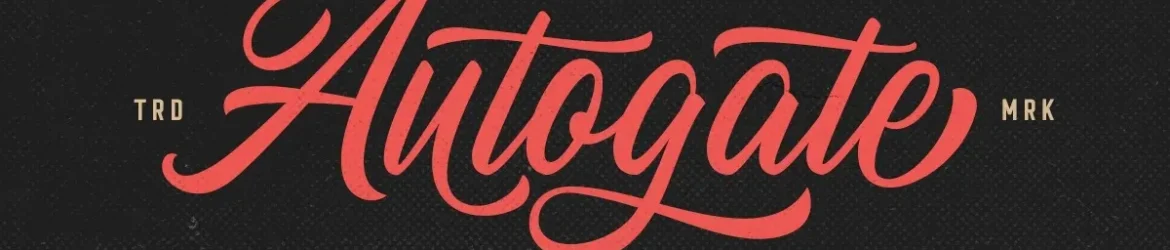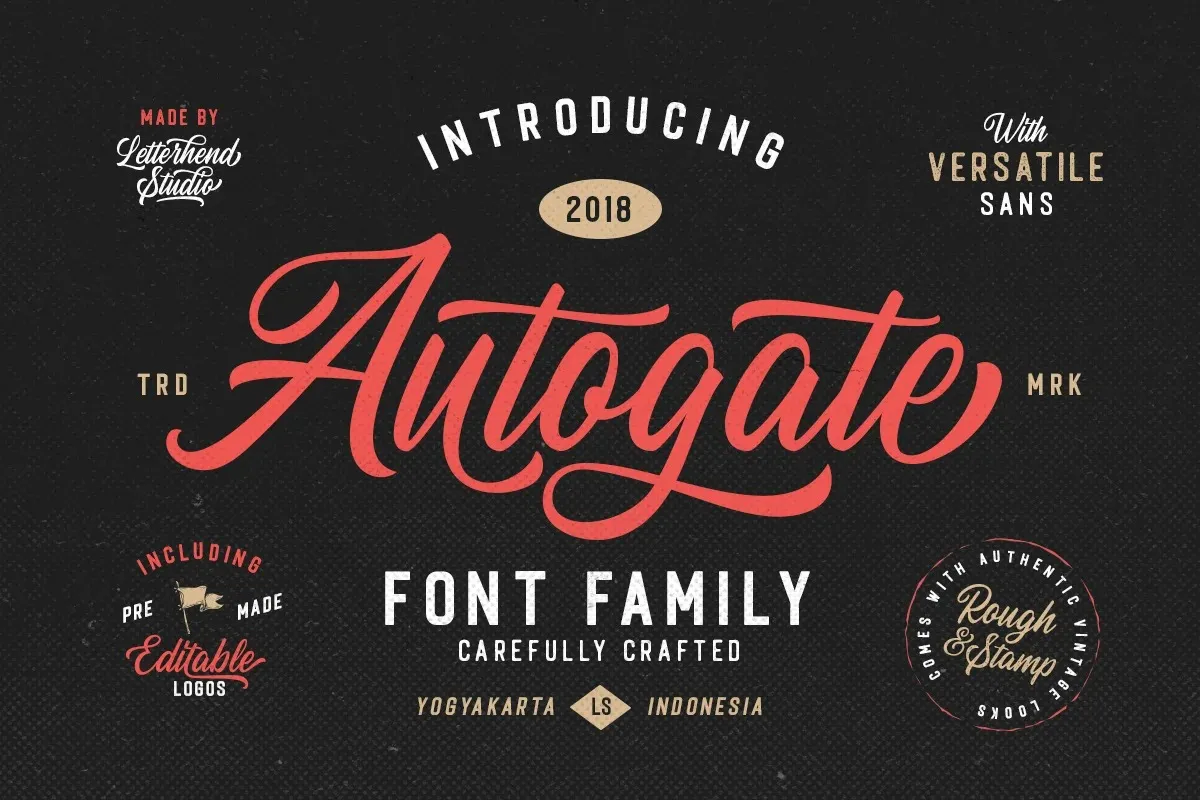
Autogate Font – Fonte Grátis
Autogate Font
A Autogate Font é uma elegante paleta de fontes escrita que surge dos lábios do Designer 99designs Letterhend Studio. Ela combina a essência clássica com um toque divertido, incorporando ligaturas e swashes para dar à sua tipografia aquele ar amigável e criativo. Essa família de fontes é perfeita para criações como logotipos, roupas, convites, marcações, embalagens e anúncios. É uma opção versátil que inclui a maioria das partes necessárias de um conjunto de fontes — desde as letras maiusculas e minúsculas até símbolos e números — tudo isso em um só lugar. Além disso, oferece set alternativos de estilos, ligações e suporte multilíngue. Com a Autogate Font, você pode escolher sua própria identidade visual ou dar um toque especial às suas criações.